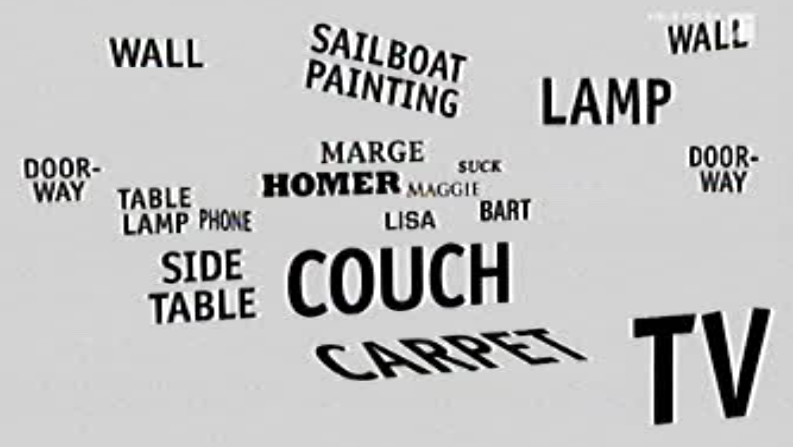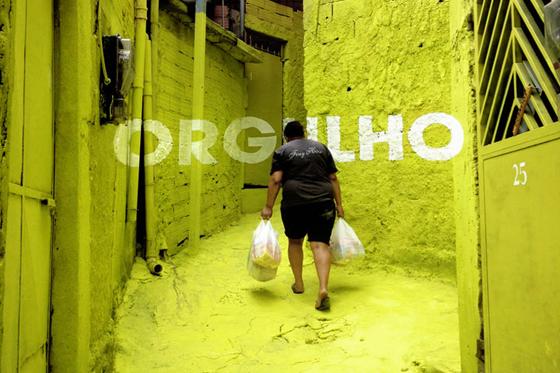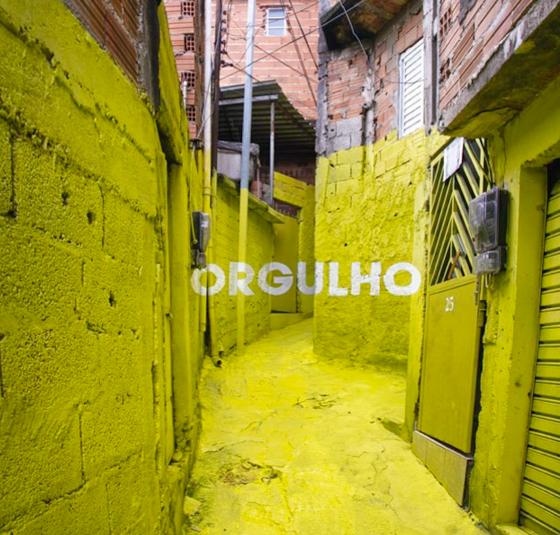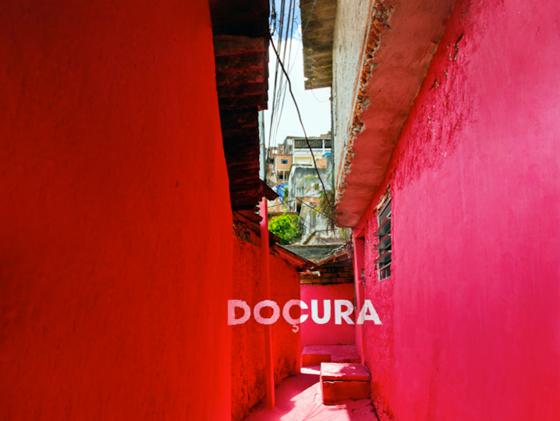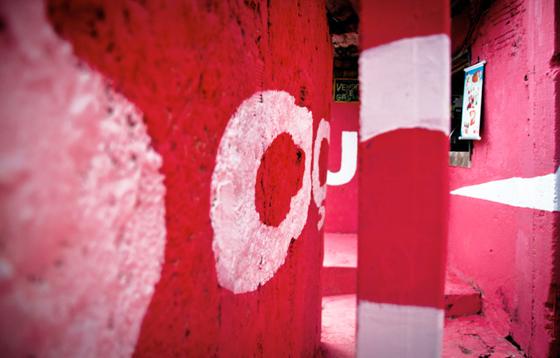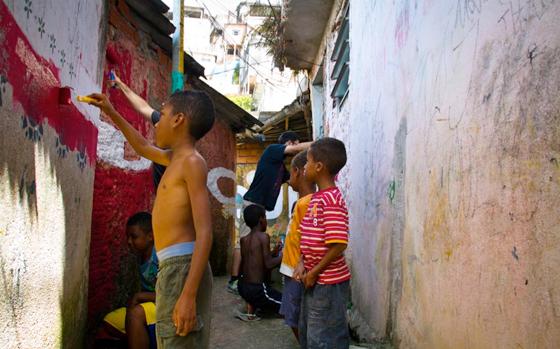
Ich habe auch einen schönen Vertipper gefunden. Bei Stern online war mal wieder Frau Schmitt-Sausen* am Werk:
Gestern noch falsch:
Heute dann richtig:
*bertel wird sich erinnern …
Und kürzlich habe ich schon mal einen gefunden, aber ich habe leider vergessen mir zu notieren, woher der Screenshot stammt:
Zum Thema Leserlichkeit war ich gerade baß erstaunt, daß man diesen Text, dessen Scan eigentlich deutlich zu gering aufgelöst ist, um einzelne Buchstaben sicher identifizieren zu können, trotzdem anhand der Wortbilder wenn auch mühsam, so doch einigermaßen sicher »lesen« kann. Ich habe das jetzt nur stichprobenweise getestet, aber bin nicht auf unüberwindbare Hürden gestoßen und habe den Verdacht, daß man möglicherweise den ganzen Text zusammenbekommen würde, wenn man sich die Zeit nähme.
Die Simpson typografisch:
Im Vorspann zur Folge „500 Schlüssel“ von letzten Dienstag. Man beachte, dass nr die beiden Eltern in Serifenschriften gesetzt sind …
Kapier ich nicht … :-?
Normalerweise sieht man an dieser Stelle im Vorspann so ein Bild:
Ah, ok. Hab ich mir noch nie angeschaut … :-)
Ja dann ist die Darstellung in Wort ohne Bild natürlich sinnlos für den Betrachter. Ich hatte erst überlegt das Vergleichsfoto gleich mit dranzuhängen, war dann aber zu faul eins zu suchen :bow:
Ha, ich habe mir gerade erschlossen, dass »suck« offensichtlich auch für »Schnuller« verwendet werden kann. :cheer: Man lernt doch täglich was Neues im Forum. ;-)
Von denen, die es besser wissen sollten …
Oh … ich muss gestehen, ich hab’ sowas noch nicht so oft gesehen und war sofort sehr begeistert. Das urban-spanische Ambiente mit der frohen Farbigkeit steigern ja noch das Seherlebnis. :-)